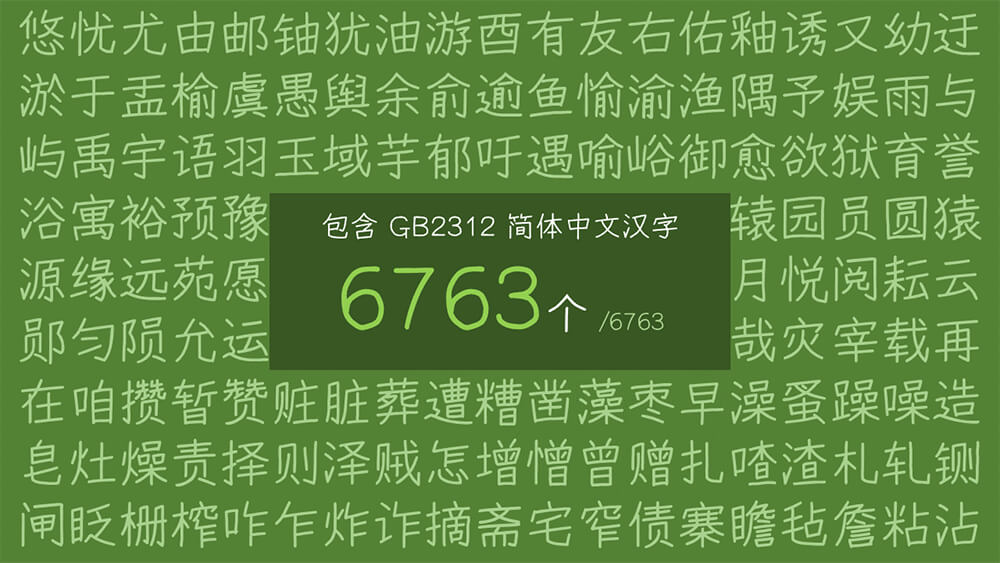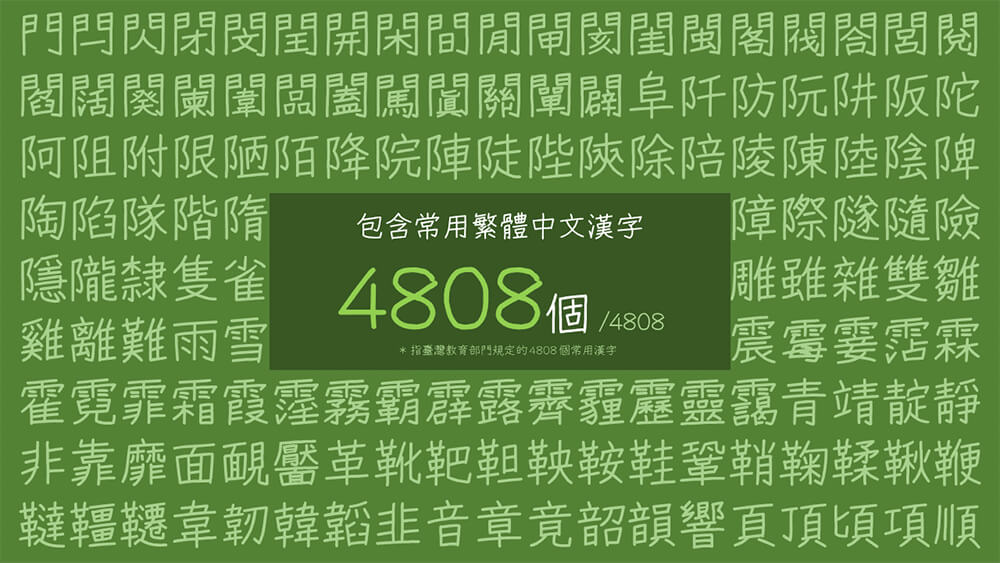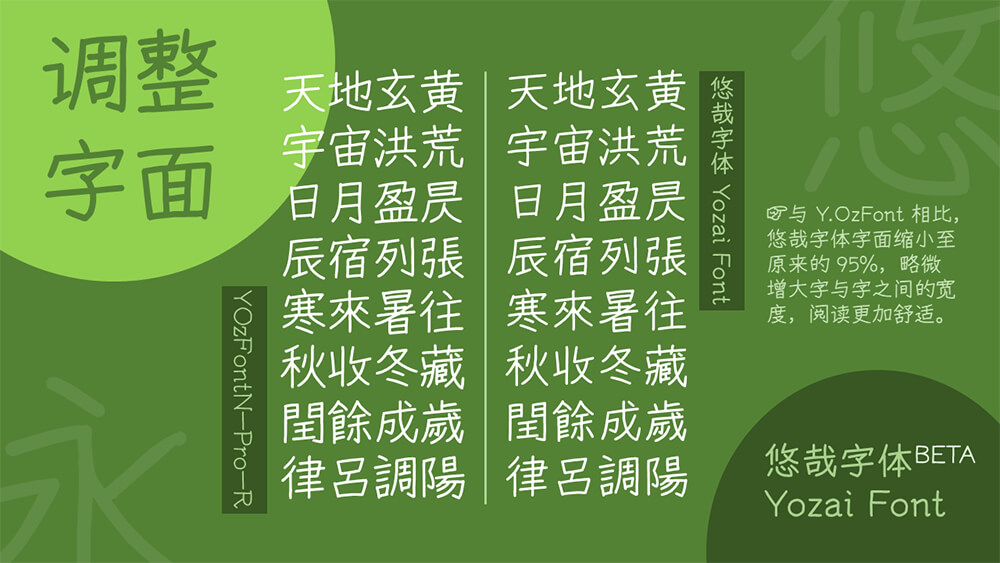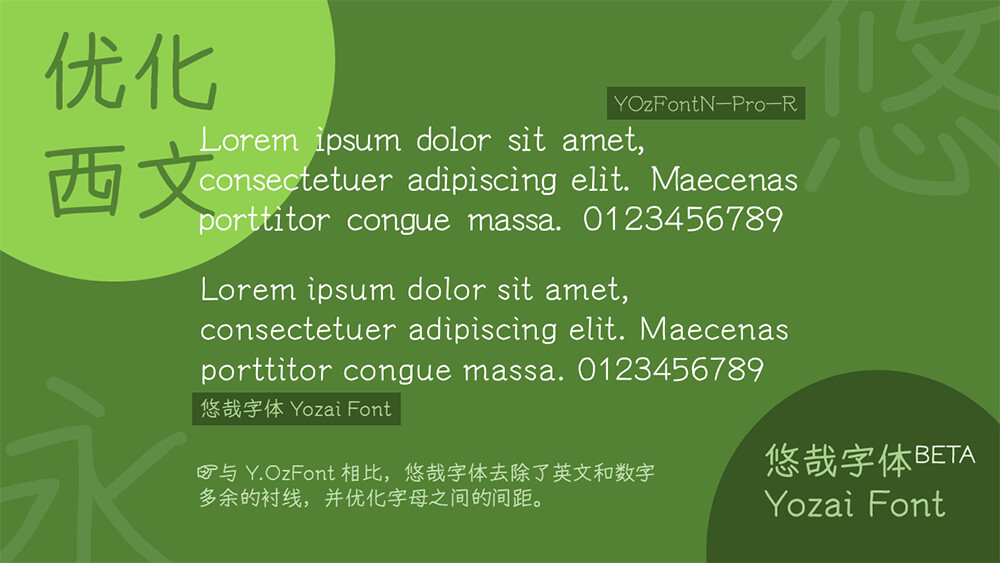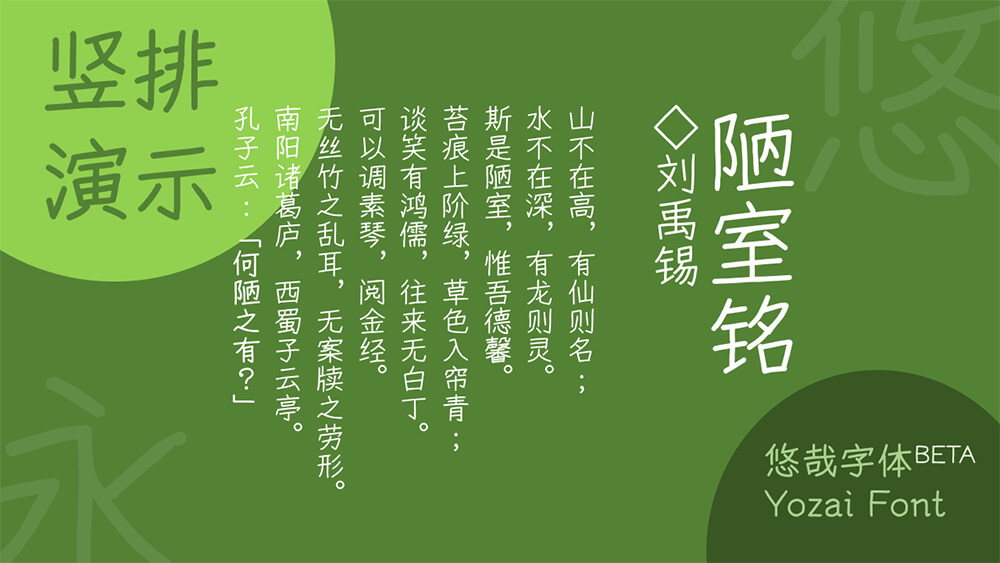
悠哉字体:一款悠游自在的可免费商用的手写字体
本字体是一款基于 Y.OzFont 的手写风格的字体。利用原字体中已有的笔划和部件,通过拼接和调整造出新字 (必要时自己用鼠标写出部件) 。目前已补全原字体中有对应繁体字的简体字、 GB 2312 范围内的所有汉字 (6763 个) 、《通用规范汉字表》范围内的所有汉字 (8105 个) ,BIG5 范围内的所有汉字 (13058 个) 。自 0.860 版本起,采用 zi2zi 深度学习补全 CJK 统一表意文字基本区 20992 字,并按需增补少量扩展区汉字。
在原 Y.OzFont 的基础上,字面缩小至原来的 95%,优化西文和标点符号的显示;修改部分汉字的写法,使其接近中国内地的规范字形。由于原版字形偏细,从 0.715 版本起,新增 Medium (中等) 字重。
自 0.717 版本起,本字体共有 4 个字重: Light、Regular、Medium、Bold;自 0.860 版本起,Bold 字重取消。
1. 本字体仍处于测试版,部分汉字还是处于日本写法,且字库并不是很全。 计划: 更正 GB 2312 内汉字的写法为中国内地的字形,补全 CJK 统一汉字基本区内的所有汉字。
• 新增 Unicode 17.0 加入的小字「儿」(U+16FF2、U+16FF3)。
• 修正以下扩 J 汉字的码位:𲸰𲾝𳄮𳇫𳋩𳋭𳋮𳋳。
• 新增扩 C+、扩 E+、扩 J 汉字:𫜺𫜻𬺭𲘥𲘿𲝻𲠀𲠍𲨔𲰹𲰼𲶹𲷇𲸰𲾝𳄮𳇫𳋩𳋭𳋮𳋳。上述汉字可在叶典查询。
• 新增特殊符号:U+FFFC、�U+FFFD。
• 调整希腊字母、西里尔字母的边距;
• 对已有的竖排标点新增映射;
• 调整 U+20DD 和 U+20DE 的宽度为 0。
• 修正「敩」U+6569 做成「𢽾」U+22F7E 的问题,并将前者原字形移到后者的码位。
• 调整以下汉字:翽讆讏躗躛𬎆;
• 调整汉字笔画区字符:㇀㇁㇂㇃㇄㇅㇆㇇㇈㇉㇊㇋㇌㇍㇎㇏㇐㇑㇒㇓㇔㇕㇖㇗㇘㇙㇚㇛㇜㇝㇞㇟㇠㇡㇢㇣,新增两个笔画字符:㇤㇥;
• 增补 YOzN 字体中包含的其他特殊符号;
• 新增表意文字描述符:⿰⿱⿲⿳⿴⿵⿶⿷⿸⿹⿺⿻⿼⿽⿾⿿㇯〾。
• 调整以下汉字字符:〦〧〨〩净唤唳奂换捩涣焕痪碌迩
• 新增 4180 个汉字,详情点此查看。本版本已补全 CJK 统一表意文字基本区,不过增补的字形大多由 zi2zi 从「霞鹜文楷」完整版深度学习生成,其中大部分字形效果欠佳,不过聊胜于无。
• 本版本起不再提供 Bold 字重,因为 Bold 字重大多数字符已经糊掉了,糊掉的粗体还不如不做,粗体直接由系统渲染实现。
• 调整以下汉字字符:〦〧〨〩净唤唳奂换捩涣焕痪碌迩
• 新增 4180 个汉字,详情点此查看。本版本已补全 CJK 统一表意文字基本区,不过增补的字形大多由 zi2zi 从「霞鹜文楷」完整版深度学习生成,其中大部分字形效果欠佳,不过聊胜于无。
• 本版本起不再提供 Bold 字重,因为 Bold 字重大多数字符已经糊掉了,糊掉的粗体还不如不做,粗体直接由系统渲染实现。
• 补全 BIG5-2003 范围内的所有 13058 汉字。 (采用简单粗暴的拼接方式补全,没有考虑设计美感。)
• 修改部分「屯」、「蚩」、「忝」等字和部件的写法(仅限常用字)。
• 修改「忳」、「籼」、「絕」、「粵」、「躇」、「勇」等字。
• 新增部分 BIG5 汉字。 (采用简单粗暴的拼接方式造字,没有考虑设计美感。)
• 新增「玁」简体「?」(U+247A4)。
• 新增苏州码子(〡〢〣〤〥〦〧〨〩)。
• 修改「瘗」、「慭」、「铏」、「眾」、「掮」、「蒋」、「虞」等字。
• 优化「觇」、「觌」、「觎」、「觏」、「觐」、「靓」等字的「见」字旁。
• 优化「场」、「杨」、「殇」、「觞」、「钖」、「旸」等字的「?」字旁。
• 优化「转」、「轮」、「论」、「输」、「瘫」、「聂」、「汇」等字的字形。
• 修改部分「者」、「尚」、「敝」、「黹」、「春」、「秦」、「奏」、「奉」、「亮」、「虎」、「兼」、「函」、「周」、「殳」、「巿」、「奚」、「臾」、「叟」、「冒」、「非」、「麻」等字和部件的写法(仅限常用字)。
• 补全《通用规范汉字表》内所有 8105 个汉字。
• 新增简繁体「biáng」字(U+30EDD/U+30EDE)、人名用字「韡」简体(U+2E9F5)。
• 新增注音符号(ㄅㄆㄇㄈ)。
• 新增易经 64 卦符号。
• 修改连接号(半破折号)「—」为占一个汉字位置的横线。
• 优化部分汉字的字形结构,如「东」、「乐」、「严」等。
• 修改部分「骨」、「氐」、「爵」、「尔」、「蚤」等字和偏旁的写法(仅限常用字)。
• 修改「隧」、「暹」等汉字中「辶」的写法。
• 重新设计「饣」字旁。
• 优化英文字母设计,使其更显圆润,更接近 Sans Serif 风格。(1/I/l 依旧区分)
• 新增《通用规范汉字表》内「浭」、「秾」、「嘚」、「跶」等 100 个汉字。
• 补全 GB2312 范围内所有汉字对应的繁体字。
• 修改部分「户」、「扇」、「扁」等字和偏旁的写法(仅限常用字)。
• 合入 Pr6N 字库。
• 新增 Light 字重。
• 补全 GB2312 范围内的所有汉字。
• 修改英文和数字为 Sans Serif 风格,并区分“l”、“I”、“1”。
• 修改部分「角」、「肖」、「平」、「半」、「丑」、「与」、「彐」、「酋」、「卷」等字和偏旁的写法(仅限常用字)。
• 新增 Medium 字重。
• 新增 GB2312 范围内「女」、「虫」、「石」、「讠」等部首的部分汉字 200 余个。
• 修改部分「曾」、「包」、「巨」、「灰」、「妥」、「夌」、「戋」、「曷」、「孚」、「䍃」、「巽」、「臽」、「鬲」、「直」、「真」、「具」、「爰」、「查」、「益」、「青」、「舀」、「俞」、「单」、「礻」、「辶」等字和偏旁的写法(仅限常用字)。